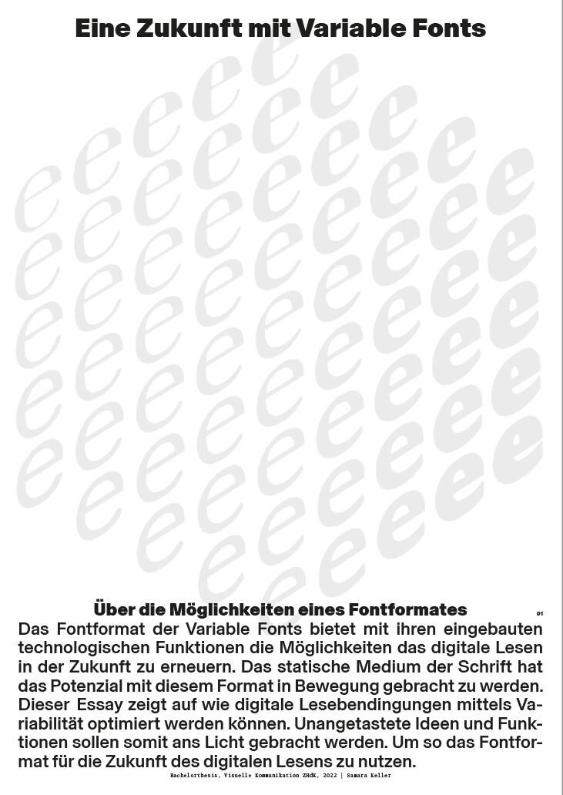
Eine Zukunft mit Variable Fonts
Weitere TitelUntertitelÜber die Möglichkeiten eines Fontformates
BeschreibungDas Fontformat der Variable Fonts bietet mit ihren eingebauten technologischen Funktionen die Möglichkeiten das digitale Lesen in der Zukunft zu erneuern. Das statische Medium der Schrift hat das Potenzial mit diesem Format in Bewegung gebracht zu werden. Dieser Essay zeigt auf wie digitale Lesebendingungen mittels Variabilität optimiert werden können. Unangetastete Ideen und Funktionen sollen somit ans Licht gebracht werden. Um so das Fontformat für die Zukunft des digitalen Lesens zu nutzen.ArchivnummerBBE-2022-C11-001